Font chữ miễn phí và font trả phí khác nhau thế nào? Nên chọn loại nào?
So sánh font chữ miễn phí và font trả phí: khác nhau về bản quyền, chất lượng Việt hóa, độ ổn định, hỗ trợ dự án thương mại và cách chọn phù hợp.
Khi bắt đầu một thiết kế, rất nhiều người có cùng câu hỏi: dùng font miễn phí có đủ không, hay nên mua font trả phí? Câu trả lời không nằm ở việc font nào “đẹp hơn” một cách tuyệt đối, mà nằm ở mục đích sử dụng, mức độ rủi ro bản quyền, yêu cầu tiếng Việt và độ quan trọng của dự án.
Một bài đăng mạng xã hội cá nhân có thể chỉ cần font miễn phí. Nhưng logo thương hiệu, bao bì sản phẩm, bảng hiệu cửa hàng, bộ nhận diện, template bán cho khách hoặc ấn phẩm in số lượng lớn thì nên cân nhắc kỹ hơn. Font không chỉ là tài nguyên trang trí; font là một phần của tài sản thương hiệu và có thể ảnh hưởng đến khả năng sử dụng lâu dài.
Bài viết này sẽ so sánh font miễn phí và font trả phí theo các tiêu chí thực tế: bản quyền, chất lượng Việt hóa, độ ổn định, khả năng dùng thương mại, hỗ trợ file thiết kế và cách chọn loại font phù hợp.
Font miễn phí là gì?
Font miễn phí là font bạn có thể tải về mà không phải trả tiền ngay tại thời điểm tải. Tuy nhiên, “miễn phí” không luôn đồng nghĩa với “được dùng mọi nơi”. Có font miễn phí cho cá nhân nhưng không cho thương mại. Có font miễn phí được dùng thương mại nhưng không cho phép bán lại, chỉnh sửa hoặc đóng gói trong sản phẩm khác. Có font được chia sẻ lại trên nhiều website nhưng thông tin license không rõ ràng.
Vì vậy, khi tải font miễn phí, điều quan trọng nhất là đọc kỹ điều kiện sử dụng. Nếu font chỉ dùng cho mục đích cá nhân, bạn không nên đưa vào logo khách hàng, bao bì bán hàng, template thương mại hoặc sản phẩm in bán ra thị trường.
Font trả phí là gì?
Font trả phí là font yêu cầu mua, đăng ký gói hoặc sở hữu quyền sử dụng theo điều khoản cụ thể. Lợi ích lớn nhất không chỉ nằm ở file font, mà nằm ở sự rõ ràng: bạn biết font được cung cấp từ đâu, dùng cho phạm vi nào, có hỗ trợ tiếng Việt ra sao và có phù hợp cho dự án thương mại hay không.
Với designer làm việc cho khách hàng, font trả phí giúp giảm rủi ro khi bàn giao file. Với chủ shop, doanh nghiệp nhỏ hoặc thương hiệu đang xây dựng nhận diện, font trả phí giúp hệ thống thiết kế ổn định hơn vì font có thể dùng lặp lại trên nhiều điểm chạm: logo, nhãn sản phẩm, bảng hiệu, menu, poster, social post và bao bì.
Khác nhau về bản quyền và phạm vi sử dụng
Đây là khác biệt quan trọng nhất. Font miễn phí có thể rất đẹp, nhưng nếu license không cho dùng thương mại, bạn vẫn có thể gặp rủi ro khi dùng cho khách hàng hoặc sản phẩm bán ra. Ngược lại, font trả phí thường có điều khoản rõ hơn, giúp bạn biết mình được phép dùng trong phạm vi nào.
Khi làm dự án thương mại, hãy tự hỏi:
- Font có được dùng cho logo không?
- Font có được dùng trên bao bì sản phẩm không?
- Font có được dùng trong file in số lượng lớn không?
- Font có được nhúng vào website, app hoặc PDF không?
- Font có được dùng trong template bán lại không?
Nếu câu trả lời không rõ, font đó chưa thật sự an toàn cho dự án nghiêm túc. Một thiết kế đẹp nhưng không rõ quyền sử dụng có thể tạo rắc rối sau này, nhất là khi thương hiệu phát triển lớn hơn.
Khác nhau về chất lượng Việt hóa
Với thiết kế tiếng Việt, chất lượng Việt hóa quan trọng hơn rất nhiều so với khi chỉ dùng tiếng Anh. Một font có thể nhìn đẹp ở chữ Latin cơ bản, nhưng khi gõ “đậm đà”, “thương hiệu”, “mỹ phẩm”, “trà sữa”, “cà phê”, các dấu có thể bị lệch, quá sát, quá cao hoặc không đồng bộ với thân chữ.
Font miễn phí đôi khi chỉ hỗ trợ một phần ký tự tiếng Việt hoặc được Việt hóa chưa kỹ. Điều này không phải lúc nào cũng xảy ra, nhưng bạn cần kiểm tra trước khi dùng. Font trả phí hoặc font có trang giới thiệu rõ ràng thường được đầu tư tốt hơn về preview, bộ ký tự, cách trình bày và thông tin phiên bản.
Trước khi chọn font, hãy gõ thử các cụm có nhiều dấu:
- Cà phê sữa đá
- Đặc sản Việt Nam
- Mỹ phẩm thiên nhiên
- Bé học chữ mỗi ngày
- Thiết kế thương hiệu
Nếu dấu bị chồng, lệch hoặc làm dòng chữ mất cân bằng, font đó không phù hợp cho dự án tiếng Việt dù nhìn đẹp ở preview.
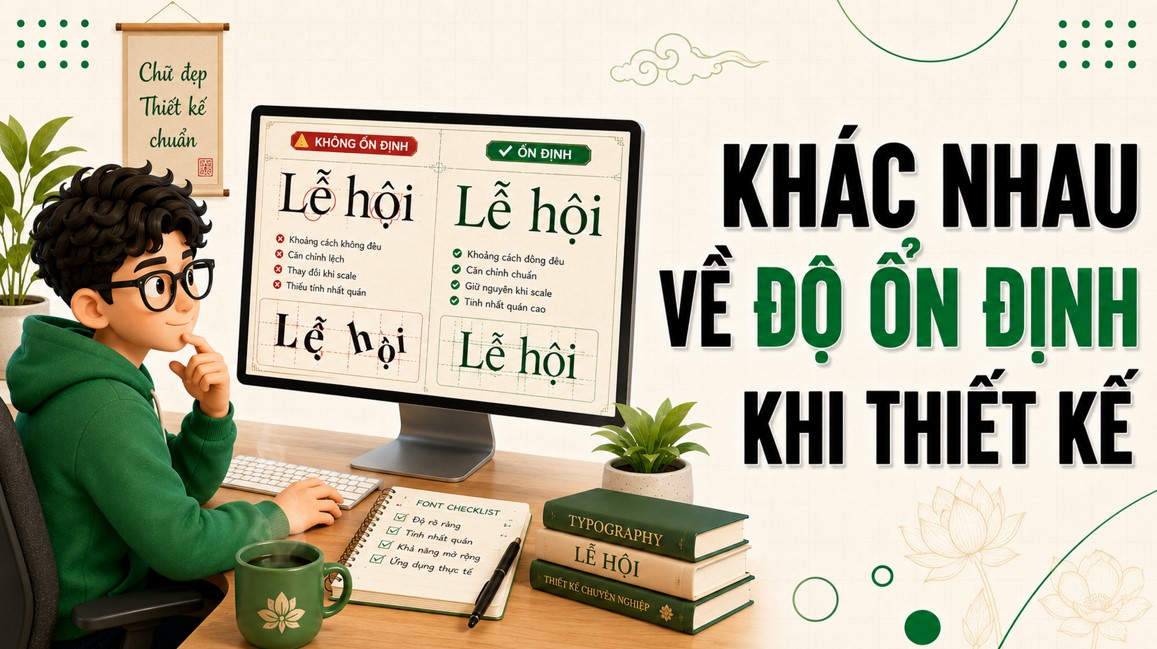
Khác nhau về độ ổn định khi thiết kế
Font trả phí thường có lợi thế về độ hoàn thiện: kerning, khoảng cách chữ, độ dày nét, bộ ký tự, chữ số, dấu câu và nhiều style đi kèm. Điều này giúp designer làm việc nhanh hơn, ít phải chỉnh thủ công từng cặp chữ.
Font miễn phí vẫn có thể dùng tốt, nhất là trong bài đăng cá nhân, thumbnail, poster thử nghiệm hoặc dự án nhỏ. Nhưng nếu bạn làm logo, menu, bao bì hoặc bộ nhận diện cần dùng lâu dài, một font ổn định sẽ tiết kiệm nhiều thời gian hơn so với việc sửa lỗi từng file.
Font miễn phí và font trả phí đều có chỗ đứng riêng. Font miễn phí giúp bạn bắt đầu nhanh, thử nhiều phong cách và tiết kiệm chi phí. Font trả phí giúp dự án thương mại an toàn hơn, ổn định hơn và có khả năng dùng lâu dài hơn.
Với thiết kế tiếng Việt, đừng chỉ hỏi font có đẹp không. Hãy hỏi font có đủ dấu không, license có rõ không, dùng thương mại được không và có phù hợp với đầu ra cuối cùng không. Bạn có thể bắt đầu bằng font miễn phí Việt hóa, sau đó nâng cấp lên gói font trả phí trên Fontdep khi dự án cần sự chỉn chu và an toàn hơn.